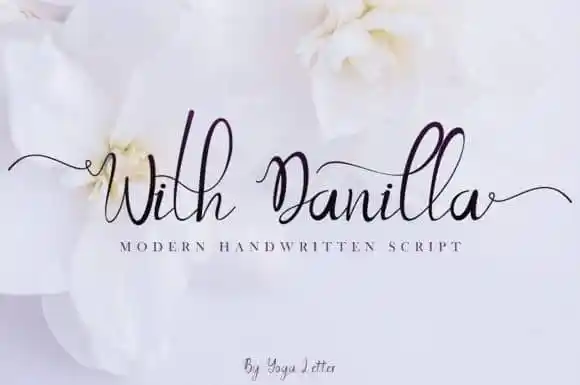
With Danilla Calligraphy Font – Download Grátis
A fonte ‘With Danilla Calligraphy Font’ é uma elegante tipografia script que abrange vários estilos alternativos. Ela se destaca pelo seu aspecto natural e sofisticado, sendo perfeita para qualquer projeto de alto nível. Desenvolvida pela designer Isroni Yoga Prasetya da plataforma 99designs, essa fonte não apenas adorna seus trabalhos de uma maneira refinada, mas também adiciona um toque de personalidade única. Com sua aparência natural e encantadora, esta fonte é perfeita para projetos que exigem um toque romântico ou elegante. Pode ser utilizada em diversas situações, como criar cartões de status nas redes sociais, anúncios de casamento, mensagens memoráveis entre amigos e familiares e até mesmo para promover produtos ou serviços. Com ‘With Danilla Calligraphy Font’, você enriquece seu trabalho, tornando-o ainda mais atraente e especial.